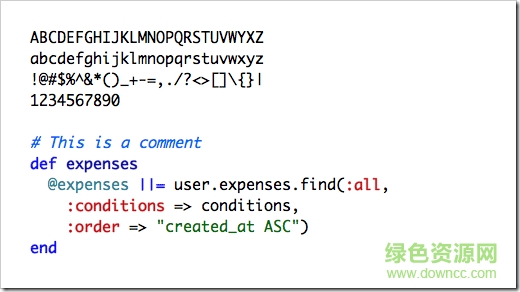
monaco字體事實(shí)上是蘋(píng)果電腦上的一款默認(rèn)字體,當(dāng)然Linux和win版系統(tǒng)也可以用,當(dāng)然也適用win7系統(tǒng),號(hào)稱蘋(píng)果出品最好的編程字體,在編程中的效果如下圖,喜歡這款字體的趕緊下載吧。
字體纖細(xì)秀美,但結(jié)構(gòu)清晰,風(fēng)格統(tǒng)一